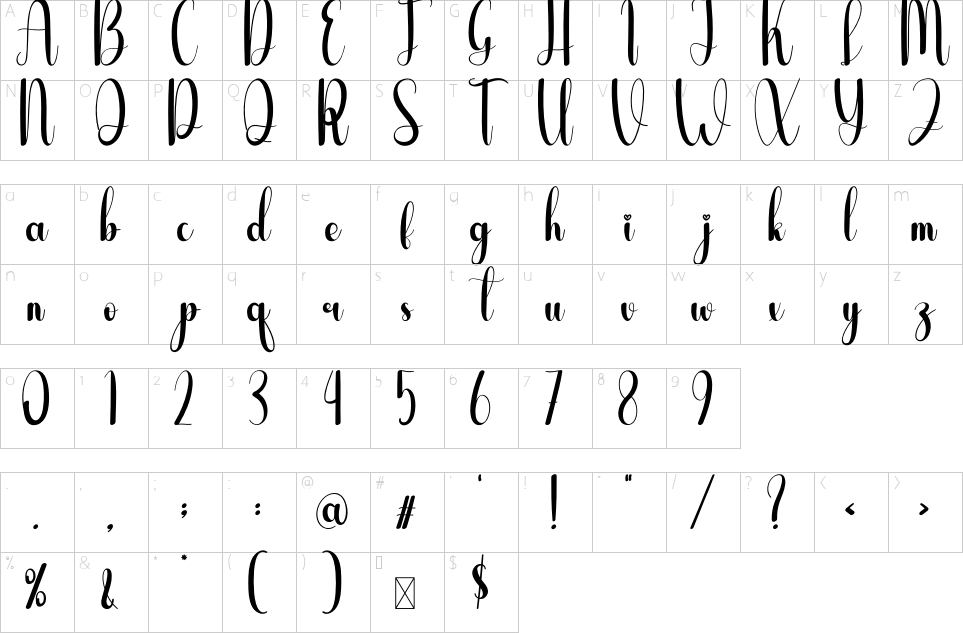
A Dragonfly é uma fonte grata que adiciona um toque especial a qualquer projeto visual. Ela foi projetada por William Jhordy e já foi baixada 203 vezes pelo público. Se você está procurando por uma fonte com um design elegante e moderno, essa pode ser sua escolha ideal para títulos ou textos de destaque em seu próximo projeto gráfico. Com a Dragonfly, você terá uma opção versátil que se adequa perfeitamente aos seus projetos, seja eletrônico ou impresso. Instalar esta fonte é fácil e rápido, permitindo-lhe explorar suas possibilidades únicas. Adicione um ar de criatividade a seu próximo projeto com Dragonfly – uma opção gratuita que merece ser testada.